1、衬线特征
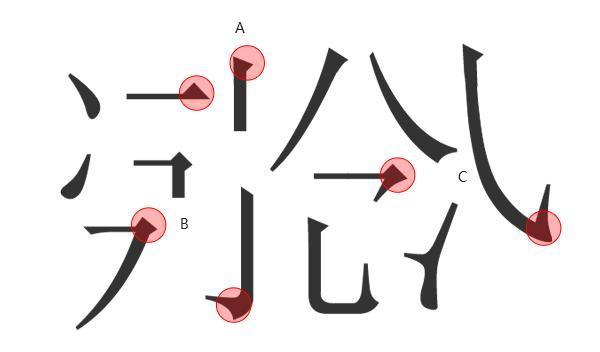
第一期我们讲到宋体是最典型的衬线字体。衬线加强法,是在了解衬线字体笔画特征的基础上加强调整的设计方法。首先我们先看看衬线体的特征(以宋体为例):
宋体衬线特征了解后,我们会发现其实衬线字体笔画很多地方装饰性元素有共性,但有些还是有个性变化的。所以我们在做不同主题的字体的时候可以根据字体特征一般在笔画的开始位置(A)、拐角(B)或是末端(C)添加装饰性元素和设计(如上图),让字体显得更加个性,更有设计感。
2、个例分析
我们先看个设计的完整稿“魔法的诱惑”。该字体是DNF女魔法师的一个转职。
1. 设计之初,先是根据游戏角色,找了魔兽世界(游戏)、画皮(魔法电影)、哈利波特(魔法电影)的字体设计做了参考。
2. 选取了造字工房的非衬线体版黑字体为原型进行设计。
选取合适的基础字体做变形是做字体设计的一个重要步骤,当然也可以在草稿上画好扫描进电脑再进行绘制也是可以的。
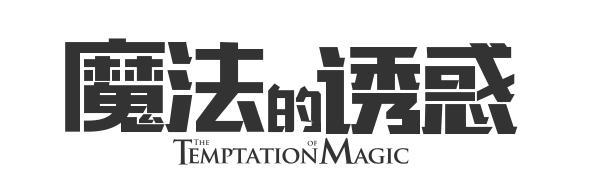
这一步已经对字体的结构和重心做了比较多的调整和变形,具体调整方法参看字体故事1。接下来讲的就是本集讲的重点,衬线加强法。
调整结构和重心的字体显然在视觉上无法满足我们的要求,这时候就要根据前面参看的游戏电影字体,添加装饰元素。
我们选取了魔法师类似巫婆的帽子、卷曲的类似枝条的形式,一些类似藤条的荆棘的元素。在笔画的开始位置(A)、拐角(B)或是末端(C)添加装饰性元素和设计。
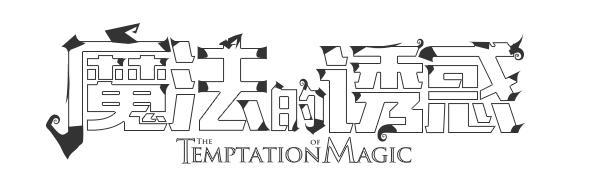
其实在什么位置上调整笔画和添加装饰性元素,有些同学可能有些迷茫,这里我举个简单的例子就很清晰了,还是拿女人做例子。女人要时尚和看起来个性如何装扮自己?
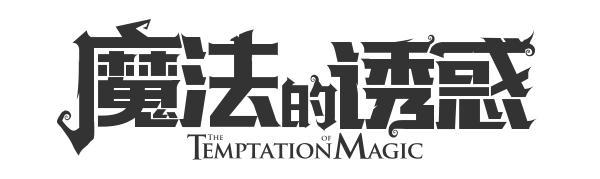
最后看看最终效果。运用同样的衬先加强法,该版本字体我也做了第二稿。不过第二稿是在把字体拉高,重心略微提上,觉得这样更符合女性的魔法特征和气息。不过最终确认还是上一版的效果。
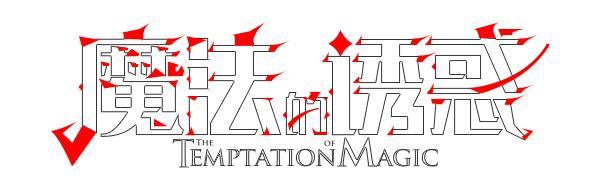
3. 类举分析
“致爱青春”是之前致青春电影刚出来时,一块游戏的活动slogan。避免统一原版字体,我这里选了极细的衬线体做原型。然后在“爱”“春”的左右添加了树叶,体现清晰、青春、校园的味道。
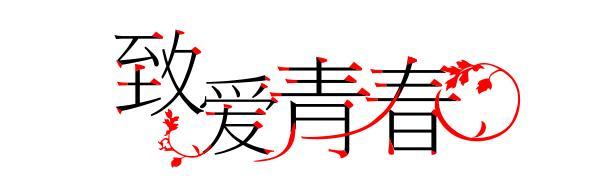
“为爱而战”是帮同事调整修改后的一个字体。比较休闲、娱乐性质的。所以稍微灵动一点的排列方式,使其看起来更加轻松活泼。在字体的笔画的很多位置加了尖角衬线效果的处理方式,加强个性和视觉冲击力。
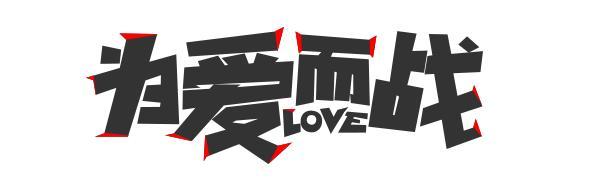
“裙下之臣”是之前做的一个游戏专题标题设计,看字体和名字就是女性类的。联想起妖媚的女性,选取了比较偏细风格的字体做变形,结合裙子,飘逸、起舞的造型对“裙”“之”“下”字的笔画做了重复和类比的装饰处理。
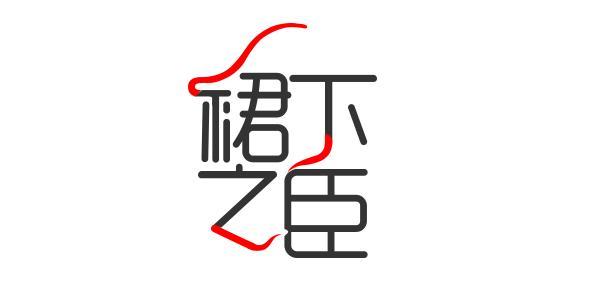
“超神英雄” 是类LOL的魔幻竞技类的一款腾讯游戏,当初是参加一个中文汉化的logo比赛做的,也同样是调整了结构和重心后添加了类似LOL字体元素的衬线元素。
“海库“需要的海洋的感觉,波涛、海浪,所以选择柔软的曲线,类似水泡的元素和浪花装饰字体笔画。
“地狱史诗” DNF的一个版本专题slogan。首页也是做了字体结构和重心调整,最后在4个字的不同笔画添加少量装饰元素使其更加个性。